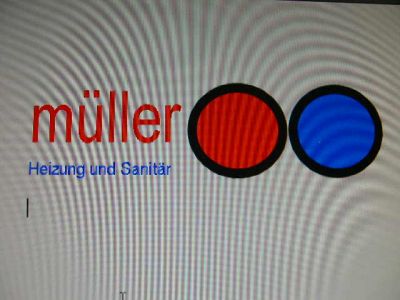
Suche passende Schrift für Sanitärlogo
Ich suche eine passende Schrift für folgendes Logo.
Sowohl für das "müller" als auch für die Subline.
Zur zeit ist das "müller" die U-bahn und die Subline die Perspective Sans
Die Firma ist ein mittelständischer Heizungs und Sanitärbetrieb.
warum musst oder willst du es denn ändern?
Ha! Eine richtig gute Frage.
Warum ist mir die nicht eingefallen?
in einem anderen Forum, welches ich von der Qualität der Antworten schätze, wurde mir der Tipp gegeben es mal mit einer anderen Schriftart zu versuchen, die mehr an Handwerk erinnert
es gibt keine schrift die an handwerk errinert.
ich würde die schriftwahl aber auch überdenken, vor allem bei »müller« die zeichen sehen nicht ausgewogen aus, da wäre die DIN schon besser aber auch nicht originell.
mh welche DIN den gibt ja tausend davon und was nehme ich für die Sub?
welche DIN den gibt ja tausend davon und was nehme ich für die Sub?
Wenn du eine grundsolide Schrift suchst, gut ausgewogen, dezent, sachlich, an die sich mit Sicherheit nach 7,3 Sekunden kein Mensch mehr erinnert, dann nimm die FF DIN.
Und für die Unterzeile? Natürlich auch DIN! Vielleicht in light. Es spricht absolut nichts dafür, zwei Groteskschriften in unmittelbarer Nachbarschaft zu mischen.
Im Übrigen finde ich die Wasserhahn-rot-blau-Punkte-Idee ganz gut, allerdings ist die Anordnung insofern etwas unglücklich, als der blaue Kreis jetzt etwas einsam steht. Also vielleicht »müller« in blau? Oder einfach die Kreise tauschen? Ja, ich weiß, links ist heißes Wasser – trotzdem.
PS: Okay, »Heizung und Sanitär«, also erst der Heizungsknopf und der muss rot sein, dann der Sanitäknopf und der muss blau sein ... aber vielleicht erst die Knöpfe und dann das »müller«?
überdenken ist nicht falsch.
die frage nach der schrift solltest du als grafiker (du bist doch einer – oder?) dir jedoch selbst beantworten. du kannst gerne eine handvoll vorschläge bringen, wenn du dich nicht entscheiden kannst. wir können dir dann gerne die eine oder andere schrift empfehlen, allerdings können wir dir die arbeit und die suche nach einem geeignetem font nicht abnehmen. generell solltest du das komplette logo überdenken, nicht von der idee her, eher von der größe, form, farbe usw. momentan ist es ja ein freefont, soll das so bleiben? welche schriften wurden dir denn in dem anderen forum vorgeschlagen?
in einem anderen Forum, welches ich von der Qualität der Antworten schätze, wurde mir der Tipp gegeben es mal mit einer anderen Schriftart zu versuchen, die mehr an Handwerk erinnert
Du hast demnach schon das richtige getan: das Forum gewechselt ;-)
Ich kann mich der Ansicht nur anschließen, dass ich die gezeigten Schriften als sehr passend empfinde; über die Zurichtung kann man sicher noch mal nachdenken. Vor allem die l’s beim müller haben rechts jeweils mehr als genug Platz, wie ich meine.
Die DIN könnte ich mir zwar auch vorstellen, aber die sieht man doch sonst auch oft genug.
> Ich kann mich der Ansicht nur anschließen, dass ich die gezeigten Schriften als sehr passend empfinde
wer sagt das? heinrich hat vollkommen recht, die momentane schrift ist
sehr unausgewogen. was sicher nicht zuletzt daran liegt, dass es ein
freefont ist.
Ich würde die beiden Punkte in jedem Fall rechts außen stehen lassen.
Das sind gute Symbole und kommen so z.B. auch im Rechnungsbogen rechts außen gut an, wenn diese Rechnung in einem Ordner abgelegt und später mal gesucht wird.
Ich würd's umstellen:
Das "müller" schmal und größer.
Darunter das Heizung und Sanitär
Und rechts daneben die Punkte größer.
So etwa (entschuldigung für die schlechte Photoqualität:
Joh..
Natürlich mit anderen Schriften und der Zwischenschlag zwischen den beiden Zeilen müßte enger. Aber so als Schmutz-Layout..
danke schonmal...
bitte versteht mich nicht falsch ihr sollt natürlich nicht meine Arbeit machen
bin noch azubi und am lernen;-)
meine frage: gibt es irgendwo übersichtsseiten der vielen 100000 Schriftarten, ich sehe bei den ganzen Seiten immer nur den Fontname aber was bringt mir das wenn ich nicht weiß wie die Schrift aussieht..
Gibt es irgendwo grundsätzlich tutorials oder anleitung für wann verwende ich welche Schrift etc?
so ich probier mal noch ein bissel rum
bleisetzer, du solltest dich in pixelsetzer umbenennen ;)
die schriften und vorallem die kreise noch etwas anpassen – passt.
aber darum gehts ja hier nicht ...
Ebend. Darum geht's ja hier nicht.
Und "ebend" schreibt man wirklich mit "d", kommt von nackenD.
(Diether Krebs, R.I.P.)
Wenn Du mir nochmal unterjubelst, daß ich Eure Gestaltungsprogramme nicht beherrsche, lasse ich Dir eine 84 p Bücher-Grotesk auf Deine Zehen fallen.
Ich muss aber zugeben, dass ich den Bedenken bezüglich Ausgewogenheit doch zustimmen muss (man sollte vielleicht doch nicht in einer fünf Minuten Kaffeepause schnell ein Logo beurteilen) — da ist noch mehr als die Zurichtung der l’s nicht perfekt.
Allerdings finde ich dennoch, dass der Charakter der Schrift sehr gut passt — ich würde mir also etwas möglichst ähnliches, allerdings etwas feiner ausgeführt suchen, auch wenn das dann nicht mehr free ist.